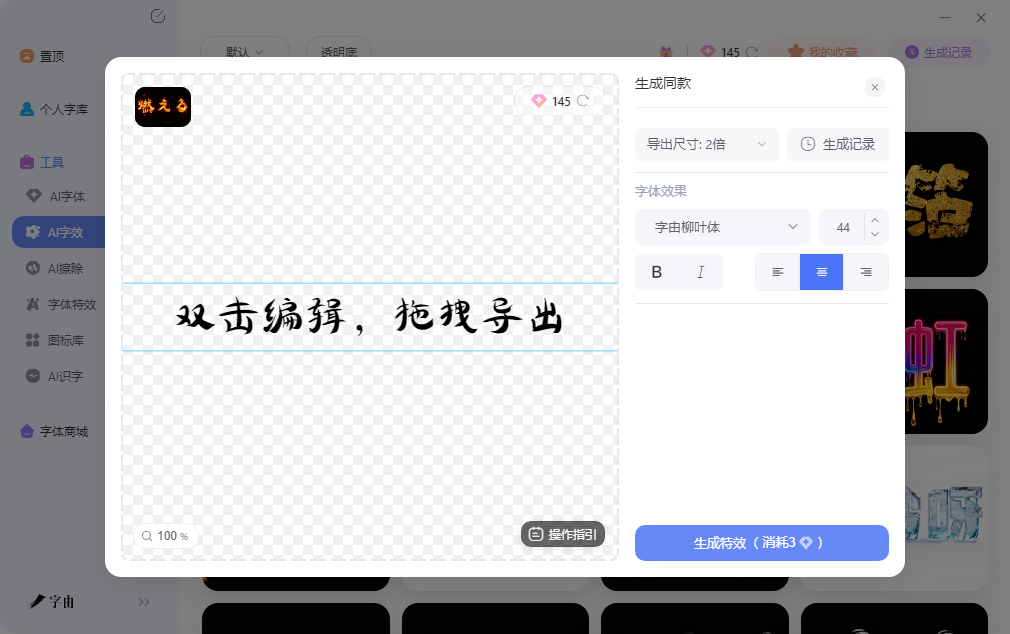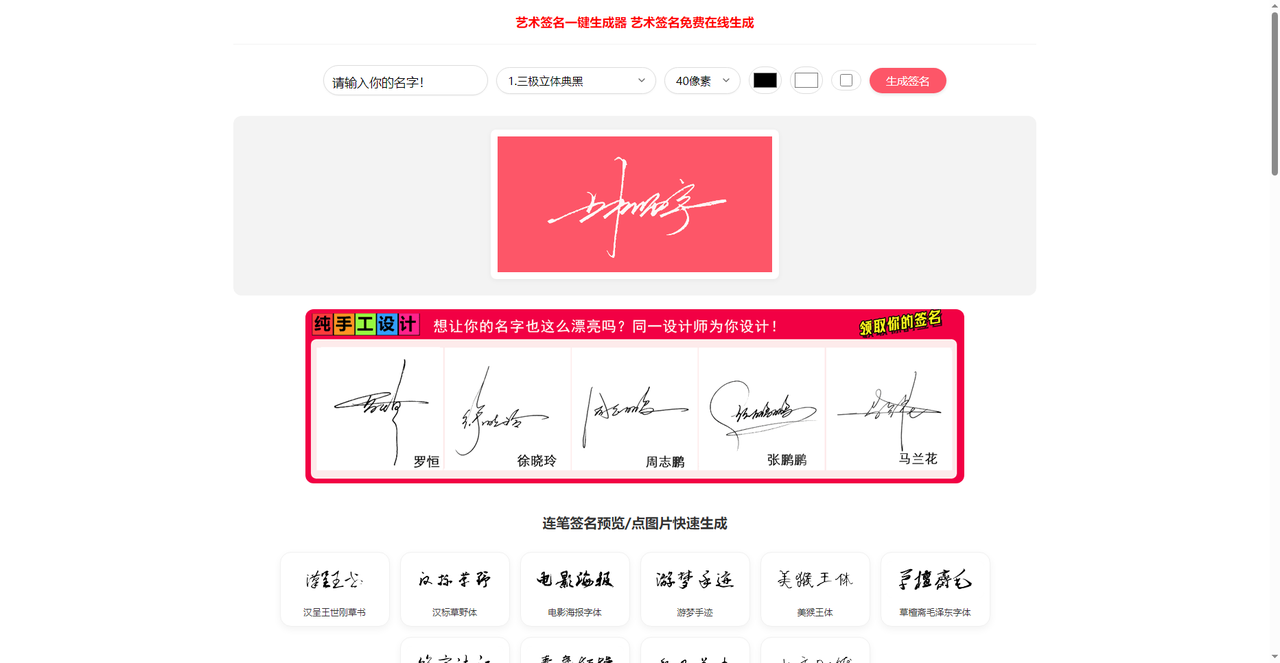
艺术签名在线生成器推荐,输入名字就能出多种风格
签合同、做名片、设计Logo时,签名往往是个人品牌的第一印象。但很多人字写得不好看,或者签名缺乏设计感,手写出来的名字放在正式文件里显得不够专业。去网上找签名设计师定制,费用从几十到几百不等,对偶尔需要签名的普通人来说不太划算。这篇文章整理的几个平台,有的专攻电子合同签名,有的偏向艺术风格渲染,有的支持中文签名生成,基本能满足从商务文件到个人品牌的签名需求。
字由不是专门的签名生成器,但AI配字和AI字效两个功能在签名设计这个场景里能组合使用。做签名前最头疼的往往是风格不确定,不知道自己的名字适合用什么字体呈现。字由的AI配字可以解决这个问题:上传一张喜欢的名片、海报或者参考图,系统会分析画面气质并推荐视觉上协调的字体选项,省去盲目翻找的麻烦。
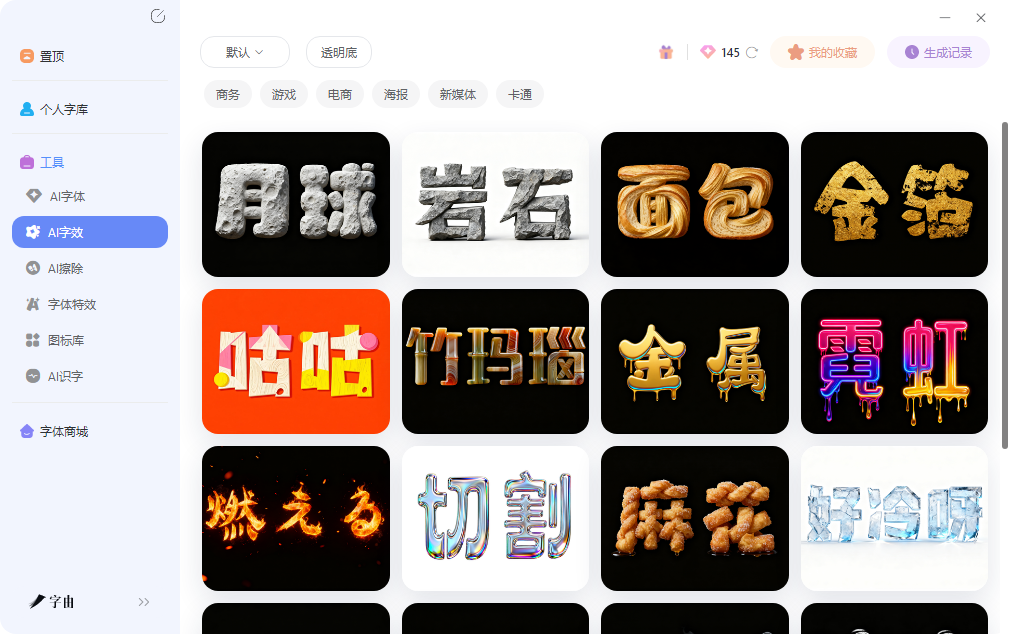
你只需要打开客户端进入AI配字界面,上传参考图或者描述签名的使用场景,系统返回几款候选字体,每款都附带预览图和风格标签。点击激活试用,在预览框里输入自己的名字,观察不同字体下的签名效果,确认气质匹配后再决定方向。这个流程比下载安装字体再打开PS试效果快得多,几分钟就能确定风格。
风格确定后,如果需要签名本身带有发光、投影或者金属效果,可以切换到AI字效。输入名字后选择特效类型,霓虹、金属、浮雕等方向都有覆盖,调整颜色、强度、光影角度后生成带透明背景的PNG图片,直接放进名片、PPT或者社交媒体头像里。登录后有一定免费额度,预览阶段不消耗,确认效果后再正式输出。
2、艺术签名在线生成器
艺术签名在线生成器是一个专注中文签名的在线工具,核心功能是把中文名字转换成多种书法风格的签名图片。输入姓名后,系统会生成行书、楷书、隶书、草书等多种书体的签名方案,每种书体下又有多个变体,比如行书就分流畅型和紧凑型,楷书分端庄型和活泼型。对于中文用户来说,这种基于传统书法的签名生成方式比西文签名工具更对口。网站支持调整签名的字号、颜色和背景,调好后实时预览,确认无误再下载。生成结果可以下载PNG图片。
3、Refont AI Signature
Refont AI Signature是一个基于AI的艺术签名生成工具,核心功能是通过深度学习模型分析你的名字结构,生成带有艺术感的签名图片。输入姓名后,系统会分析笔画特征和字形结构,生成多种艺术风格的签名方案,包括水墨风格、金属切割、霓虹发光、几何拼接等方向。每种风格都有独特的视觉处理方式,比如水墨风格带有笔触飞白,金属切割则有棱角分明的工业感。这个工具对想做个性化签名、用于社交媒体头像或者个人品牌Logo的人来说很实用。传统签名设计需要找设计师定制,Refont AI Signature通过AI模型在几秒钟内就能出图,省去了等待时间。
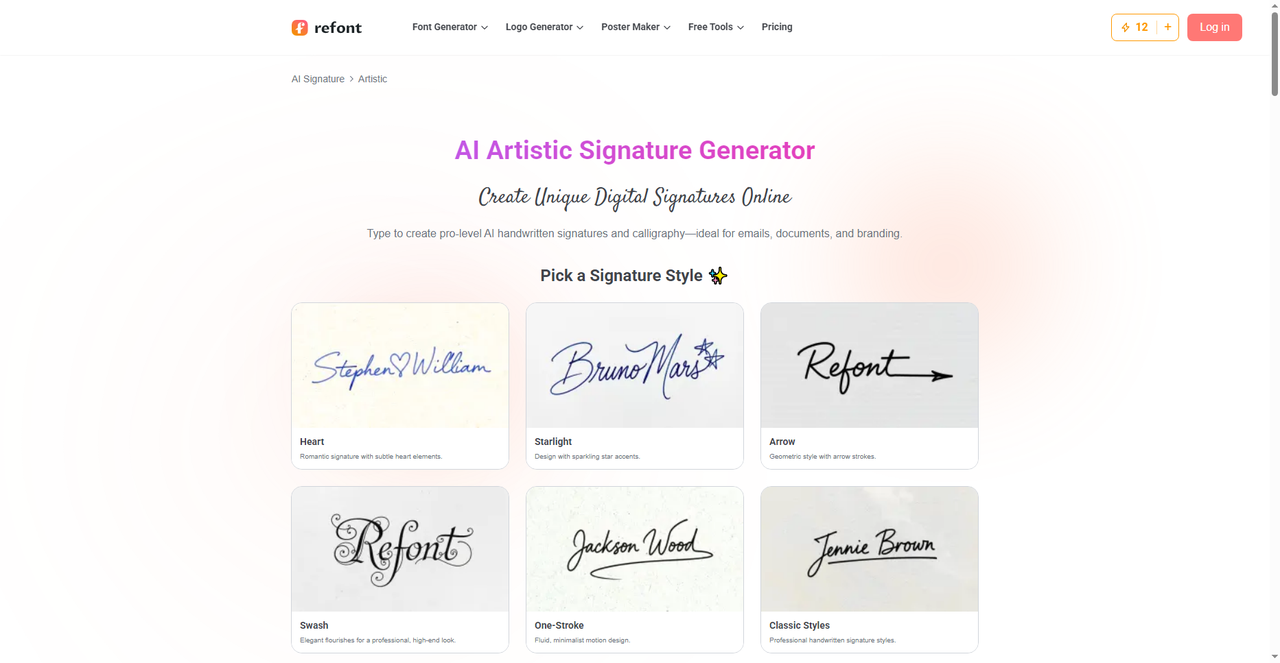
4、Signaturely
Signaturely的定位偏向商务电子签名,核心功能不是生成艺术字,而是帮你创建具有法律效力的电子签名。进入网站后可以通过三种方式创建签名:手写输入、上传图片、打字生成。手写输入支持鼠标或者触控板直接书写,系统会优化笔画流畅度;上传图片则是把已有的手写签名扫描件数字化;打字生成则是输入名字后选择字体风格,系统自动渲染成签名样式。这个工具对经常需要签合同的商务人士很实用。生成的电子签名可以直接嵌入PDF文档,支持批量签署和发送,省去了打印签字再扫描回传的繁琐流程。
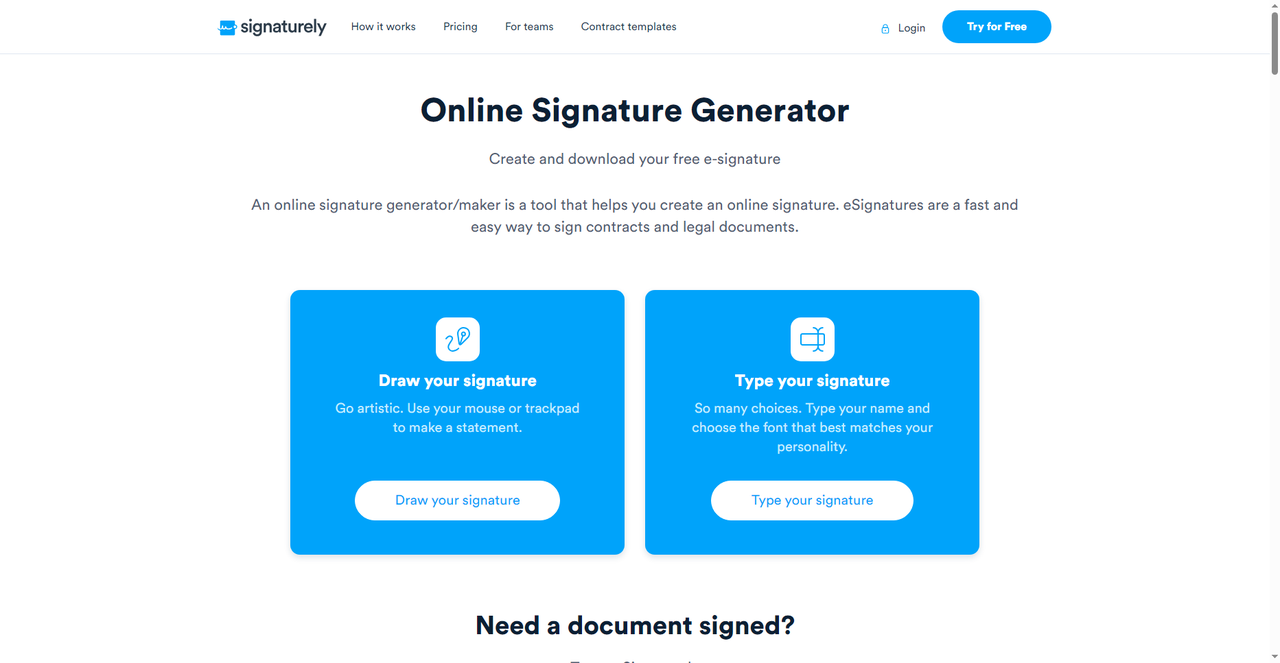
5、Signature Generator
Signature Generator是一个专门做电子签名的在线工具,核心功能是把你输入的名字转换成多种手写风格的签名图片。进入网站后输入姓名,系统会生成十几种不同风格的签名方案,包括连笔草书、商务楷书、艺术花体等方向。每种风格都有细微差别,有的笔画更粗,有的连笔更流畅,有的倾斜角度更大,可以横向对比挑出最满意的那一款。网站支持调整签名的倾斜角度、笔画粗细和字间距,调好后实时预览,确认无误再下载。生成结果可以下载PNG图片,透明背景,直接放进Word文档、PDF合同或者名片设计稿里。
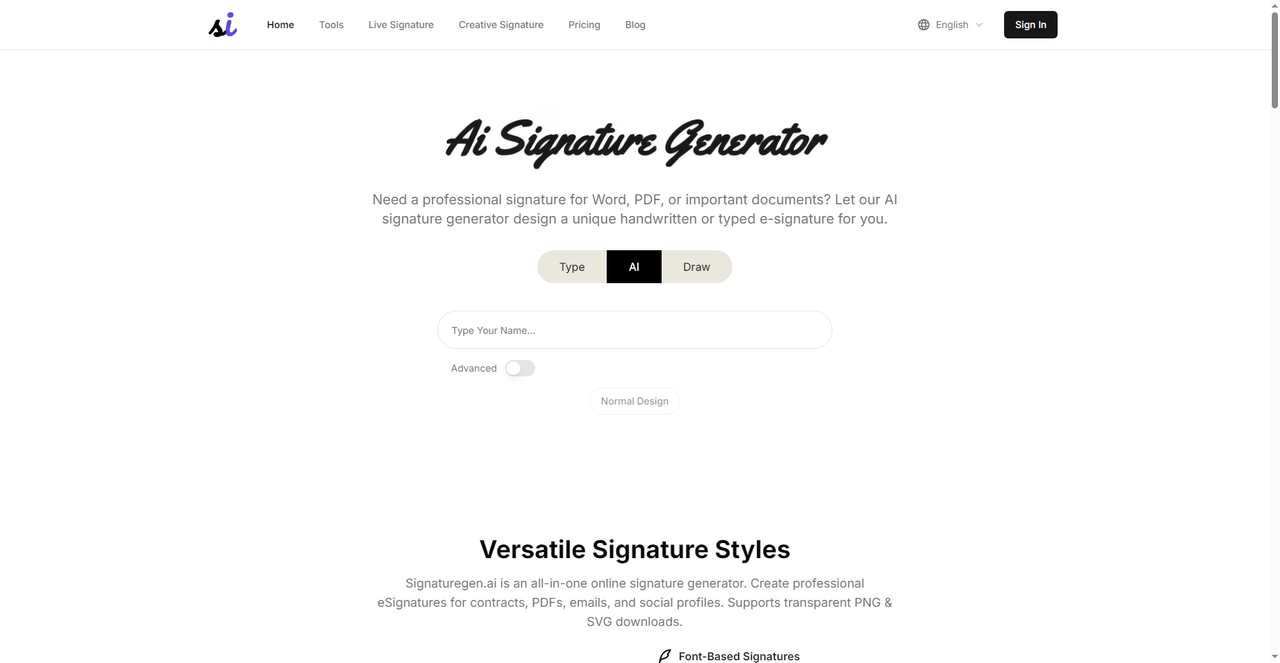
Signaturely适合商务合同的电子签署,Signature Generator适合多种手写风格的快速生成,Refont AI Signature适合艺术感强的个性化签名,艺术签名在线生成器适合中文书法风格的签名。字由在字体风格匹配和特效渲染方面提供了更系统的支持,从确定字体风格到出特效签名图都能在客户端内完成。按自己的使用场景来选,商务文件用Signaturely比较规范,个人品牌用Refont AI Signature比较有设计感,中文签名用艺术签名在线生成器比较对口。偶尔做几张签名图用网页工具足够,长期做设计可以搭配字由的字体库一起用,签名字体的选择会更丰富。